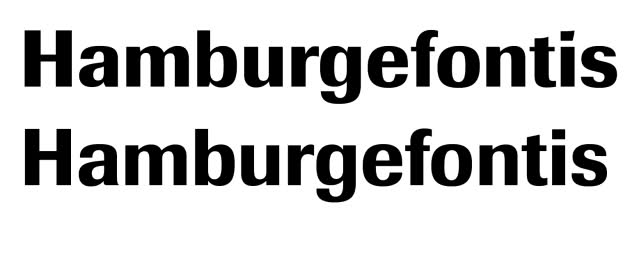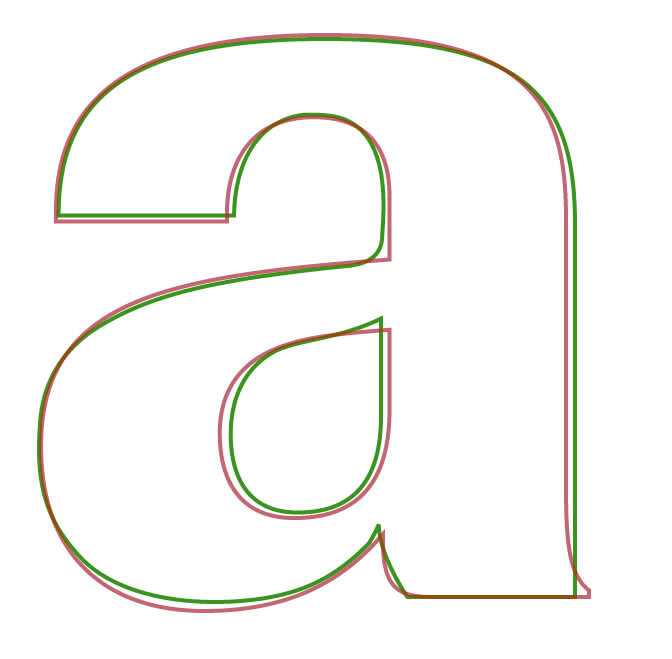
Weiterentwicklung ...
Hallo Forum
ich habe mir nach langem Überlegen die Mühe gemacht, eine Schrift nach zu zeichnen/neu zu zeichnen. Es ist die Imago (Halbfett). Ich wollte ihren Charakter erhalten, sie aber gleichzeitig verjüngen. Jede einzelne Glyphe(!) habe ich verändert, Kerning etc. neu aufgesetzt, ein eigenes Grundraster zur Hilfe genommen und den Stil wo nur möglich angepasst (leichter, moderner).
Jetzt würde ich sie gerne veröffentlichen, zögere aber noch, da ich zu wenig Ahnung von der rechtlichen Seite habe. Kann mir jemand dabei helfen?
rot = Imago / grün = neu
zunächst mit einem Wacom in Illustrator die Schrift nach-gescribbelt. Erst grob, dann feiner, um sich in die Strich- und Linienführung einzuarbeiten. Dann mit dem Pfadwerkzeug wieder die Scribbles nachgezeichnet. Dabei hatte ich jeweils die Referenzglyphe daneben stehen.
Im Hintergrund hatte ich mir ein Raster gelegt für die neuen oberen und unteren Strichstärken der Bögen, der neu versetzten Mitte usw.
Da ich mit den Verhältnissen der Verdickung nicht zufrieden war, habe ich mit dem Illustrator eine Anpassung zwischen der Imago Medium und der Bold vorgenommen und dann auf Basis dieser Anpassung gearbeitet.
Gleichzeitig mit dem Pfadnachzeichnen hab ich auch die Stilanpassungen vorgenommen, wie zum Beispiel der Auslauf beim kleinen a oder der Schulteransatz bei n, m, g. In einigen Fällen war es auch nötig, zusätzliche Vertiefungen einzuarbeiten, damit eine Stelle nicht optisch zu dick aussieht.
my two cents:
ich denke schon das man sowas machen darf, auch wenn es berthold sicher nicht gefallen wird.
was ich mich frage: wozu? ich meine, brauchen wir solch einen font? die imago ist jetzt nicht der font, der ohne ende benutzt wird – so das man eine 'imago next' bräuchte. wäre es nicht besser gewesen du steckst die kraft und zeit in einen anderen, noch eigenständigeren font? mag sein das die details für dich und ein paar andere typophile ganz interessant sind, aber die breite masse wird wohl eher die imago benutzten, wenn überhaupt. sie riecht halt noch immer etwas nach den 80s. mittlerweile gibt es ja massig solcher grotesken und diese sind auch moderner und ausgebauter. :?
Aaaalso:
Grundsätzlich unterliegt der Originalschriftentwurf der Imago erstmal dem Urheberrecht. Der Urheber kann über sämtliche Verwertungen seines Werkes selbst bestimmt. Das Urheberrecht läuft in Deutschland 70 Jahre nach dem Tod des Urhebers aus.
Theoretisch müsste man also bei einer Adaption der Imago die Erben Günther Gerhard Langes um Erlaubnis fragen.
Natürlich kann man ein Werk auch so weit verändern, dass ein komplett neues Werk im Sinne des Urheberrechts entsteht, aber das ist ja hier nicht der Fall. Die Schrift soll ja bewusst der Imago ähnlich sein.
Soweit die Theorie. Ob so ein Urheberrecht auf Schrift vor Gericht durchsetzbar ist, ist eine andere Frage.
Mit Berthold ist das auch so eine Sache. Eigentlich gibt es diese Firma nicht mehr und somit auch keinen Kläger, der dir deine Schrift untersagen könnte. Allerdings gibt es die Berthold Direct. Corp in den USA, die sich als Rechtsnachfolger sieht, jede Menge Markenrechte an Berthold-Schriften hat und auch als extrem prozessfreudig gilt. Selbst FontShop hat sie bereits verklagt. Da sollte man also seeehr vorsichtig sein. :tutor:
... was also, würdest Du mir raten?
Gedacht ist übrigens keine kommerzielle Verwertung und es soll auch bei diesem einen Schnitt bleiben!
Ob kommerziell oder nicht, spielt ja für den vermeintlich »geschädigten« keine Rolle. Entweder verdienst du Geld mit dem Werk anderer Leute, oder Du verteilst selbiges kostenlos, obwohl es eigentlich beim Originalhersteller gekauft werden soll. Beides kann gleichermaßen ärgerlich sein.
Meine (rein persönliche) Empfehlung wäre: Nimm die Schrift für deine Projekte, gib sie eventuell anderen Designern persönlich, aber stell sie nicht zum Kauf oder kostenlosen Download irgendwo ins Netz. Wie Robert ja schon sagt: Es wartet im Prinzip ohnehin niemand darauf.
... oder sie nun in einem weiteren Schritt soweit von der Imago weg zu bringen, dass sie nicht als Plagiat gilt ...?
Von einer schlechteren Kopie würde ich in dem Fall aber nicht sprechen.
Er präsentiert es ja nicht als neue Schrift, sondern als eine Überarbeitung – wie bereits angemerkt, als eine Art eine Imago Next. Darin liegt ja letztlich auch die Problemösung: Unregelmäßigkeiten und Schwächen im originalen Schriftentwurf wurden überarbeitet. Ob es das tatsächlich braucht, steht natürlich auf einem anderen Blatt.
Im Falle von Berthold wäre ich allerdings auch eher vorsichtig, was die Verbreitung des Fonts angeht.
Bitte nicht nur halb zitieren! Es hieß korrekt …
Grundsätzlich unterliegt der Originalschriftentwurf der Imago erstmal dem Urheberrecht. […] Ob so ein Urheberrecht auf Schrift vor Gericht durchsetzbar ist, ist eine andere Frage.
Und genau so ist es auch. Ein Werk (Zeichnung, Foto, Lied, Schriftentwurf etc.) unterliegt in unseren Gefilden automatisch dem Urheberrecht – allein durch die Schaffung des selbigen. Die rechtliche Durchsetzbarkeit im Streitfall steht auf einem anderen Blatt.
einen Urheberschutz beanspruchen können.
Man kann noch weiter fragen: Warum hat eine Brotschrift — trotz möglicherweise monatelangen Feilens — keine Schöpfungshöhe, aber wenn irgendjemand in Sekundenbruchteilen mit seinem Telephon ein halbscharfes Photo von seinem Frühstück oder seinem Hamster macht, entsteht ein Urheberrecht und er kann bei mißbräuchlicher Verwendung munter abmahnen. Da sind die Gewichtungen schon sehr ungleich verteilt.